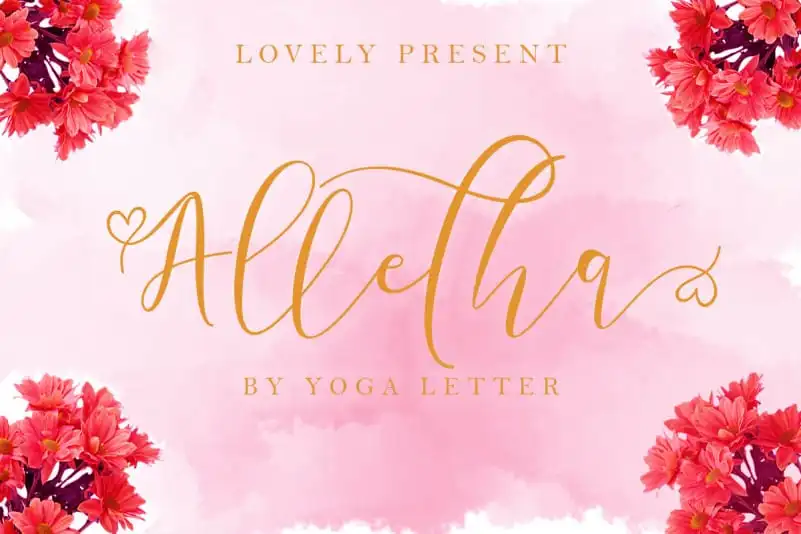
Alletha Calligraphy Font
A fonte “Alletha Calligraphy Font” é uma elegante escolha para quem busca estilo e sofisticação em seus projetos digitais. Desenvolvida pelo designer Yoga Letter, essa script moderna está disponível na categoria de Fonts Script, perfeita tanto para uso profissional quanto pessoal. Ideal para a criação de eventos especiais como casamentos, onde você pode transformar qualquer design em algo único e memorável, desde convites até decorações. Seja para promover os produtos ou serviços que oferece, seja para acompanhar sua viagem ou registrar momentos especiais com seus amigos mais próximos. O uso desta fonte é também ideal para a promoção de diferentes espaços turísticos, como villas e hotéis, tornando seu conteúdo ainda mais chamativo. Além disso, ela se destaca em qualquer projeto que exija um toque único no interior ou qualquer outro tipo de negócio, oferecendo uma variedade de opções personalizadas. Além do valor estético, a “Alletha Calligraphy Font” também é de alta qualidade e muito atrativa. Suas características precisas garantem legibilidade perfeita em todos os tipos de tamanhos e formatos de texto, tornando-a uma fonte que se destaca no mercado digital atual.